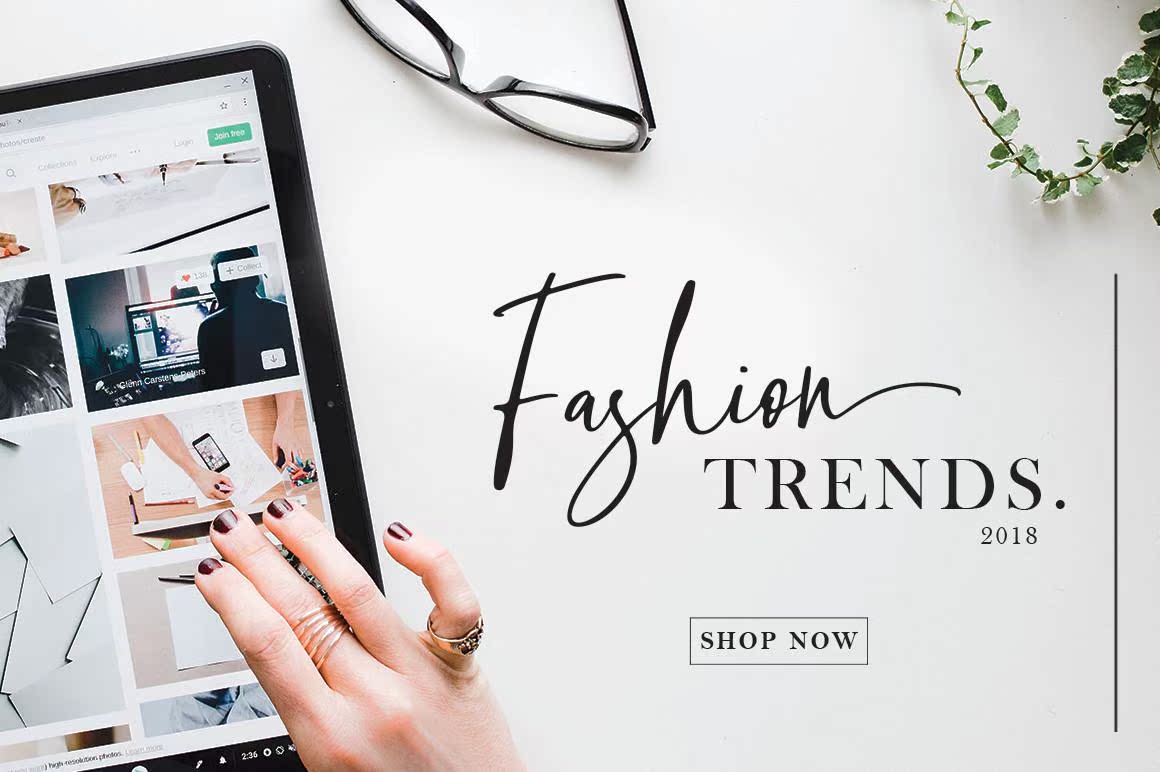
Mellyanascript是自由流动、女性化、时尚化和友好型。Mellyanascript是时尚、电子商务品牌、潮流博客或任何想成为经典和时尚的企业的代言人。Mellyanascript是自由流动、女性化、时尚化和友好型。Mellyanascript是时尚、电子商务品牌、潮流博客或任何想成为经典和时尚的企业的代言人。